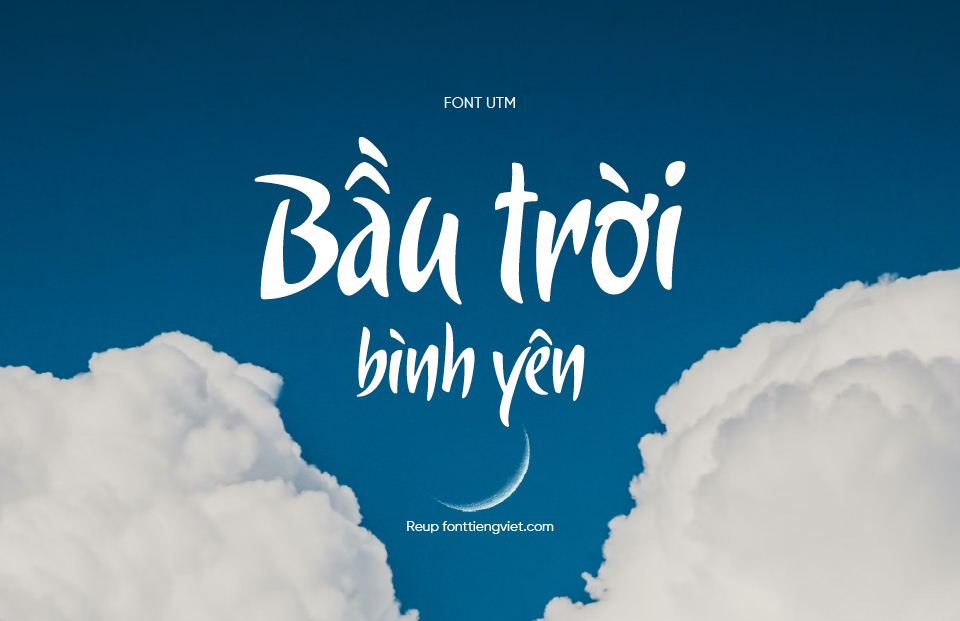
Font Việt hóa UTM Candombe
Giới thiệu về Font Việt hóa UTM Candombe
Trong thế giới đồ họa hiện đại, việc tìm kiếm một Font Miễn Phí độc đáo để tạo điểm nhấn cho các tác phẩm nghệ thuật luôn là ưu tiên hàng đầu. Font Việt hóa UTM Candombe chính là sự lựa chọn hoàn hảo nhờ phong cách thiết kế phóng khoáng và tràn đầy năng lượng. Đây là bộ phông chữ được chuyển ngữ chỉn chu, giúp người dùng dễ dàng gõ tiếng Việt có dấu mà không lo lỗi hiển thị. Với các đường nét uốn lượn tự nhiên và độ đậm nhạt linh hoạt, Candombe mang đến một hơi thở vừa cổ điển vừa hiện đại, cực kỳ phù hợp cho các bạn học sinh, sinh viên và giáo viên trong việc trang trí bảng tin hay trình chiếu bài giảng điện tử.
Đặc điểm nổi bật của bộ Font Việt hóa UTM Candombe
Phong cách thiết kế sáng tạo
Font Việt hóa UTM Candombe nổi bật với cấu trúc chữ viết tay không theo quy tắc gò bó, tạo cảm giác thân thiện và gần gũi. Các ký tự được chăm chút tỉ mỉ, hỗ trợ tốt cho các phần mềm thiết kế phổ biến như Photoshop, Canva hay bộ công cụ Microsoft Office. Điều này giúp các bài thuyết trình tại nhà trường trở nên sinh động và cuốn hút hơn đối với người xem.
Ứng dụng đa dạng trong đời sống
Bộ phông này thường được sử dụng rộng rãi trong thiết kế thiệp mời, bìa sách, nhãn dán thủ công và các dự án sáng tạo cá nhân. Nhờ tính tương thích cao, Font Việt hóa UTM Candombe giúp người dùng tiết kiệm thời gian chỉnh sửa mà vẫn đảm bảo tính thẩm mỹ cao nhất cho sản phẩm cuối cùng.